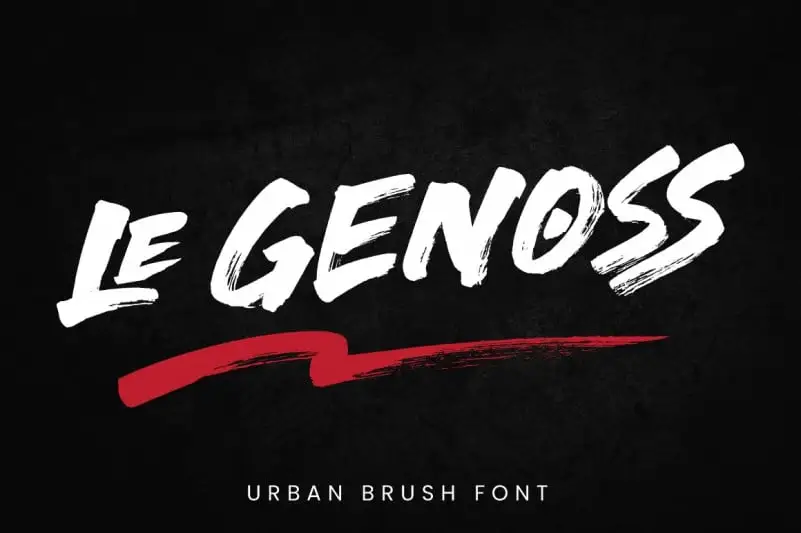
le Genoss Brush Font – Download Grátis
A le Genoss Brush Font é uma elegante escolha para designers que buscam adicionar um toque autêntico à suas criações digitais, especialmente no estilo urbano e handwritten. Desenvolvida através do uso de um pen a lousa, esta fonte urbanizada se inspira na arte da churrascaria real, oferecendo uma textura imersiva que complementa perfeitamente designs como letras grandes em outdoors ou adesivos para festivais. Criada pela estúdio Attype Studio, essa fonte de estilo brush é perfeita para aqueles que desejam incorporar um ar de urbanidade genuíno às suas mensagens digitais. Seja para criar design gráfico moderno e dinâmico ou para adicionar uma personalização única a elementos gráficos em sites e aplicativos, le Genoss Brush Font será um aliado valioso no seu conjunto de ferramentas. Com sua textura realista e estilo urbano, essa fonte atende perfeitamente às necessidades de designers que procuram uma opção criativa para seus projetos. Ela é ideal para o uso em identidade visual, logotipos e mensagens digitais, adicionando ao design um toque único e autêntico característico da cultura urbana.